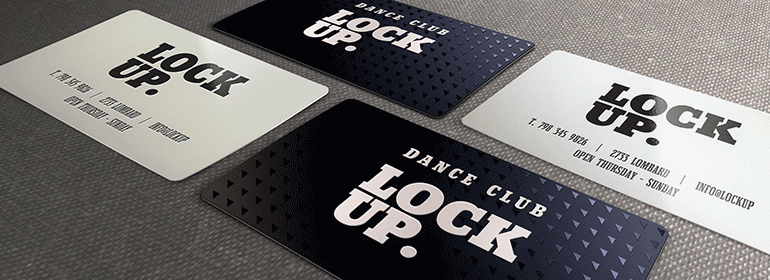
Beton™
Beton™,这款字体结构工整、笔画清晰,兼顾美观与易读性,适用于标题、正文、海报、包装、LOGO 等多种场景。字形优雅稳定,风格百搭耐看,适配日常排版与创意设计,让文字呈现更舒适、更具质感。Beton™一笔一画,皆是细节,以均衡的比例、流畅的线条打造舒适视觉体验,字形端正大气,风格简约现代。无论是商业设计、品牌宣传还是日常排版,都能轻松驾驭,让文字更有格调与力量。Beton™字体下载。
字体品牌: Linotype(Monotype) 设计师:Jost,Heinrich 字体分类:衬线体 字体属性:外文 字符集:Unicode 发布时间: 2018
Beton Extra Bold原本是为American Type Founders设计的。Beton Extra Bold是一个厚重的粗衬线显示设计。
Beton Extra Bold was originally designed for American Type Founders. The Beton Extra Bold font is a heavy slab serif display design.